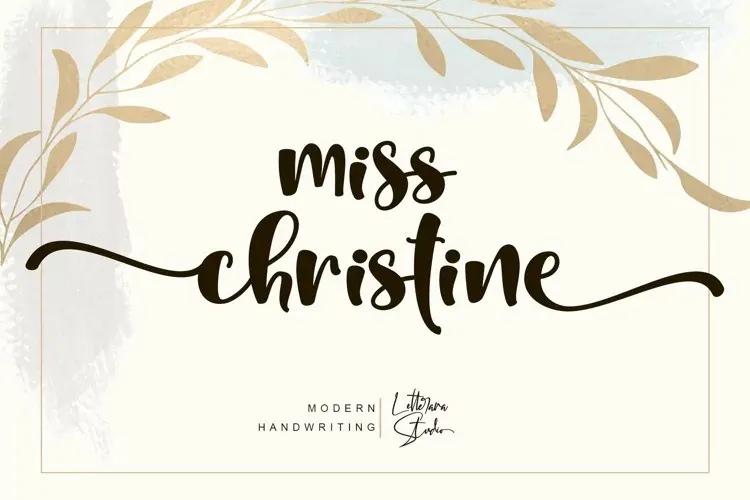
A Miss Christine Font é uma elegante e versátil fonte de script perfeita para aqueles que buscam criar designs únicos e românticos. Seu charme multifacetado abrange desde cartões de felicitações até headlines, tornando-a uma escolha ideal para projetos criativos de todas as espécies. Suas variações incríveis permitem acesso fácil a todos os seus elementos, como as alternativas de caracteres e ligaturas especializadas, garantindo que cada projeto seja único e envolvente. Além disso, o PUA encoding da font oferece uma experiência de utilização excepcional, permitindo você explorar com facilidade seu rico conjunto de símbolos e desenhos chamados “swashes”, tornando seus conceitos mais vivos. Esta font se destaca não apenas por sua aparência delicada e atraente, mas também pela sua flexibilidade na criação de designs que vão do simples aos complexos. Com o Miss Christine Font da 99designs em seu arsenal, os designers podem explorar o máximo do seu potencial criativo.